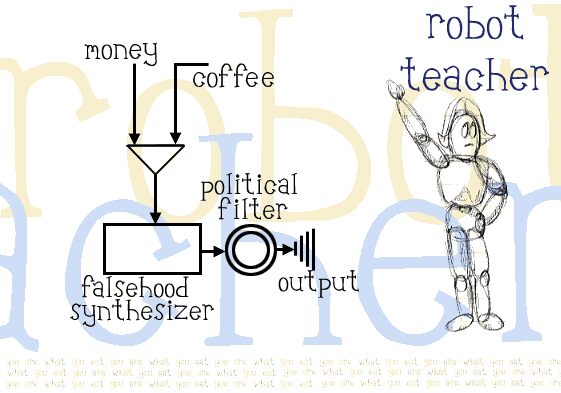
Robot Teacher, bezpłatny, groovy font display od Toma Murphy’ego 7, łączy nostalgię za szkolnymi ławkami z retro-klimatem. Wyróżnia się wysokimi, lekko rozszerzonymi literami i luźnym, przyjaznym rytmem. Kształty sprawiają wrażenie nieco domowych i inspirowanych stylem połowy wieku, a miękkie krzywizny, długie pionowe linie i delikatne szeryfy sprawiają, że alfabet wygląda zabawnie, a nie sztywno.
Sprawdzi się na plakatach szkolnych, okładkach książek dla dzieci, w ręcznie stylizowanym brandingu, nietypowych opakowaniach i tytułach, gdzie potrzebny jest ciepły, nieco dziwaczny głos. Jako darmowy font, jest szczególnie odpowiedni do krótkich nagłówków, imion i grafik tematycznych, ponieważ te smukłe litery i zaokrąglone formy błyskawicznie nadają charakteru.